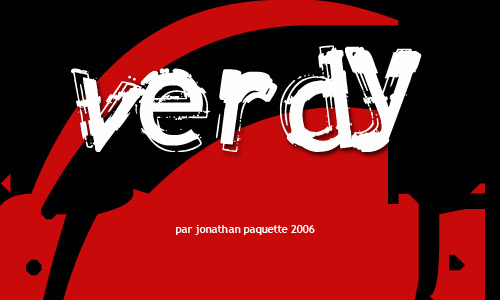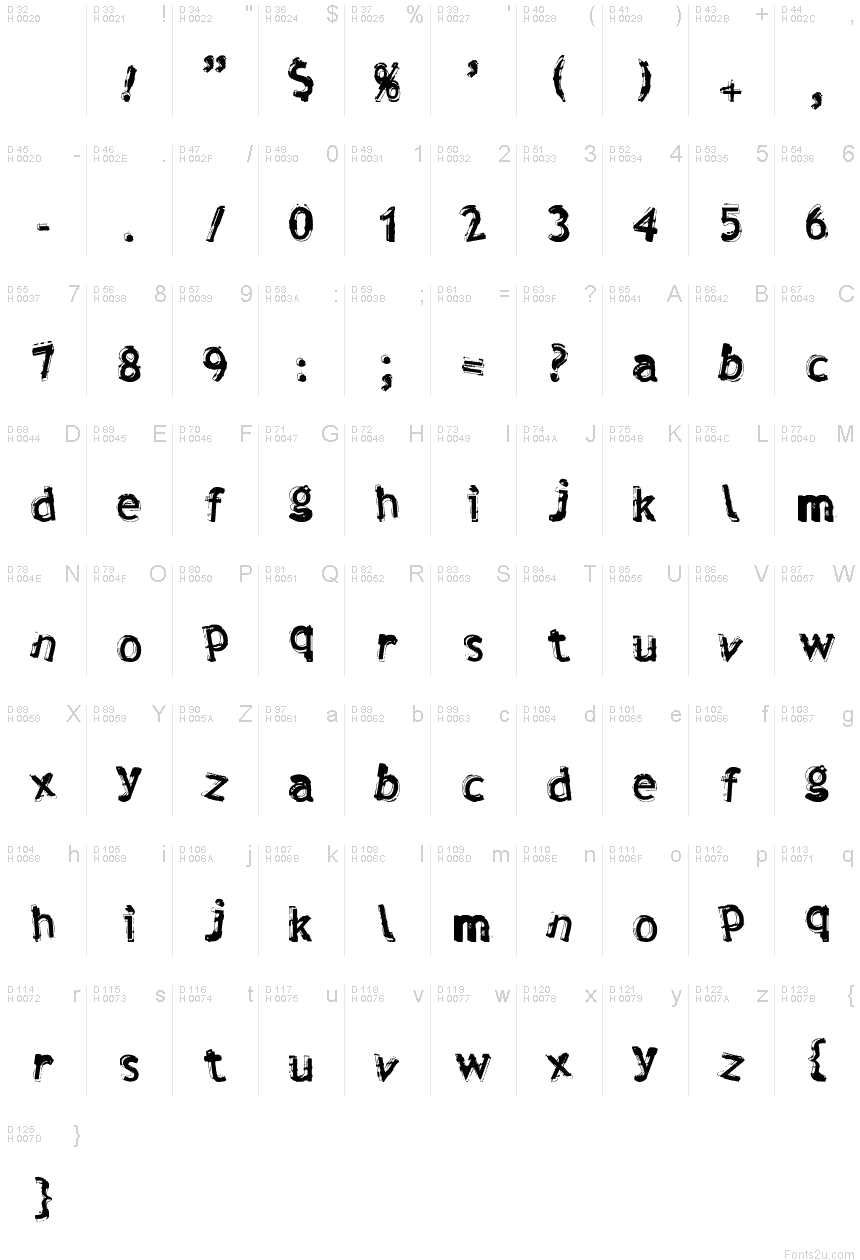
Verdy هو خط مجاني بتصميم 3D بنمط الجرونج (grunge)، يتميز بمظهر مهترئ وغير متماثل يشبه ملصقات الشوارع. تبدو الحروف كأنها مرسومة بفرشاة خشنة وممتلئة قليلاً، بينما تضفي الظلال المسحوبة بأسلوب السكتش والحواف المتآكلة على الخط ككل طابعاً حيوياً وعفوياً كأنه مصنوع يدوياً.
هذا يجعل الخط مناسباً بشكل طبيعي للمجلات المستقلة (zines)، وملصقات موسيقى الإندي، ورسوم التزلج، وعناوين الأغلفة والبطاقات، حيث تبدو اللمسات النهائية النظيفة مقيدة أكثر من اللازم. كخط مجاني، يتألق Verdy في النصوص القصيرة والجذابة وفي الهويات البصرية المتحررة، لأن تأثير الـ 3D الخشن يمنح حتى الكلمات البسيطة حضوراً صاخباً يشبه قصاصات الكولاج.